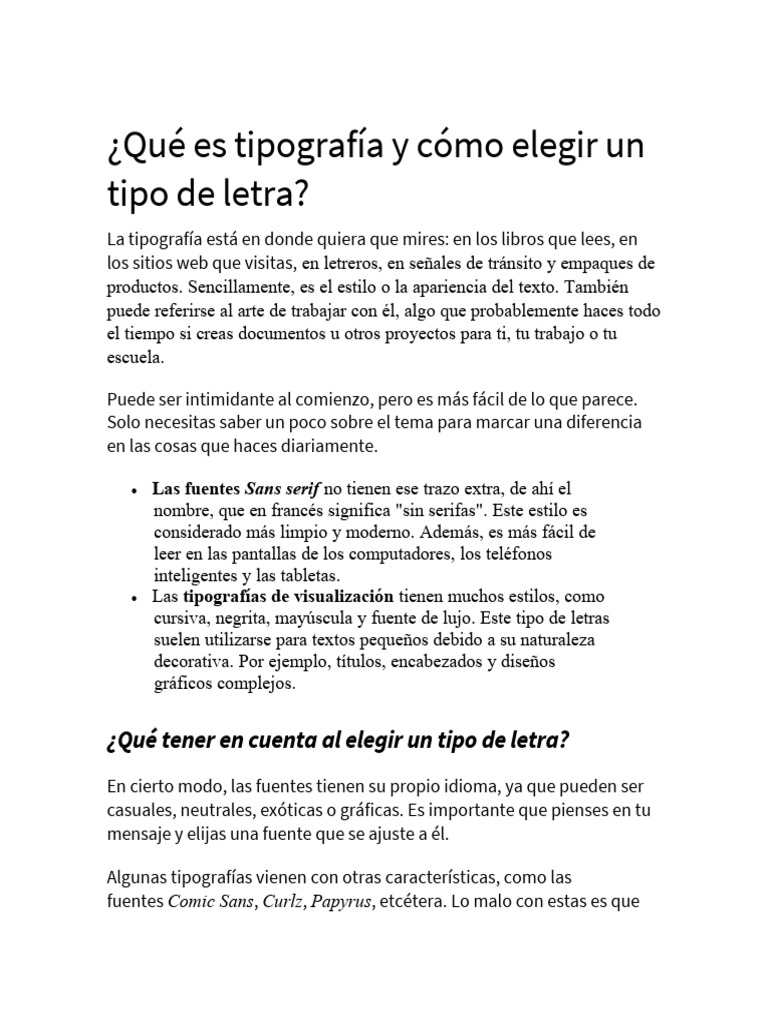
¿Qué es tipografía y cómo elegir un
tipo de letra?
La tipografía está en donde quiera que mires: en los libros que lees, en
los sitios web que visitas, en letreros, en señales de tránsito y empaques de
productos. Sencillamente, es el estilo o la apariencia del texto. También
puede referirse al arte de trabajar con él, algo que probablemente haces todo
el tiempo si creas documentos u otros proyectos para ti, tu trabajo o tu
escuela.
Puede ser intimidante al comienzo, pero es más fácil de lo que parece.
Solo necesitas saber un poco sobre el tema para marcar una diferencia
en las cosas que haces diariamente.
Las fuentes Sans serif no tienen ese trazo extra, de ahí el
nombre, que en francés significa "sin serifas". Este estilo es
considerado más limpio y moderno. Además, es más fácil de
leer en las pantallas de los computadores, los teléfonos
inteligentes y las tabletas.
Las tipografías de visualización tienen muchos estilos, como
cursiva, negrita, mayúscula y fuente de lujo. Este tipo de letras
suelen utilizarse para textos pequeños debido a su naturaleza
decorativa. Por ejemplo, títulos, encabezados y diseños
gráficos complejos.
¿Qué tener en cuenta al elegir un tipo de letra?
En cierto modo, las fuentes tienen su propio idioma, ya que pueden ser
casuales, neutrales, exóticas o gráficas. Es importante que pienses en tu
mensaje y elijas una fuente que se ajuste a él.
Algunas tipografías vienen con otras características, como las
fuentes Comic Sans, Curlz, Papyrus, etcétera. Lo malo con estas es que
tienen la reputación de estar pasadas de moda y sobreutilizadas. Si las
quieres usar, piénsalo dos veces y considera buscar otra opción. Hay
muchas fuentes con apariencias similares y con menos probabilidades
de desviar tu mensaje.
Al decidir qué fuentes usar, menos es más. Es decir, es mejor limitarte a
una o dos fuentes por proyecto. Por ejemplo, si necesitas más contraste,
intenta repetir tus fuentes en un tamaño, peso o estilo diferente. Este
truco es bueno para crear combinaciones interesantes y funcionales.